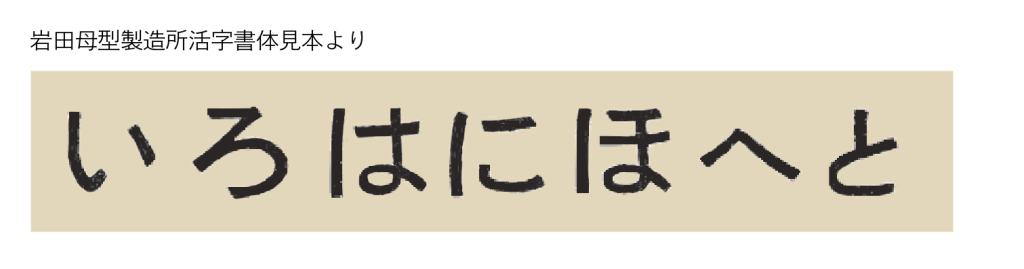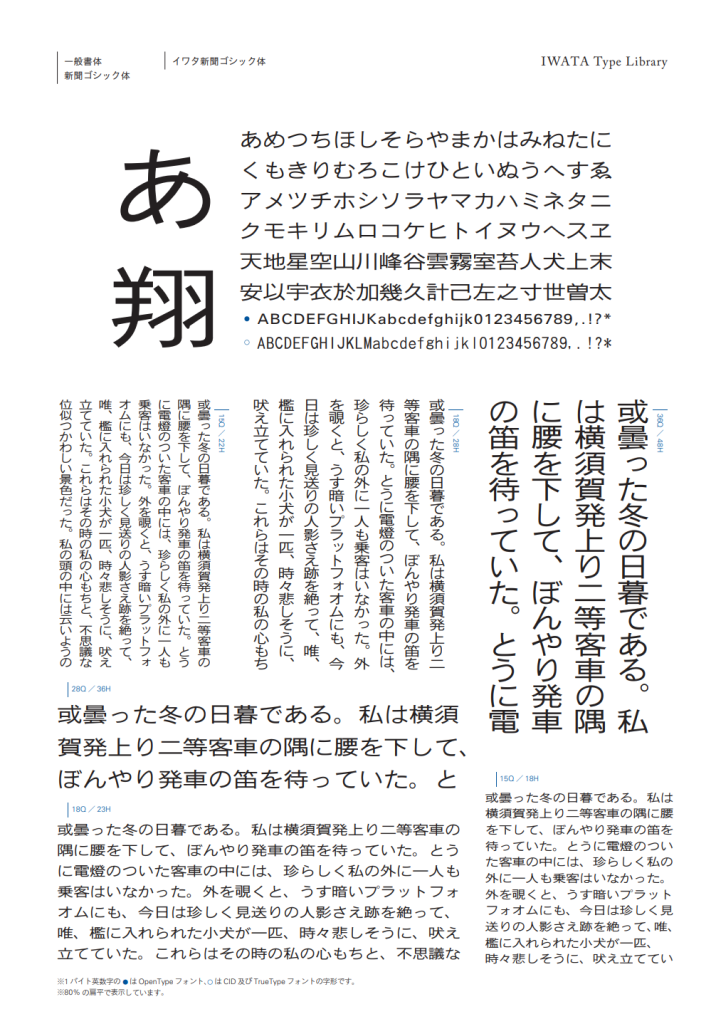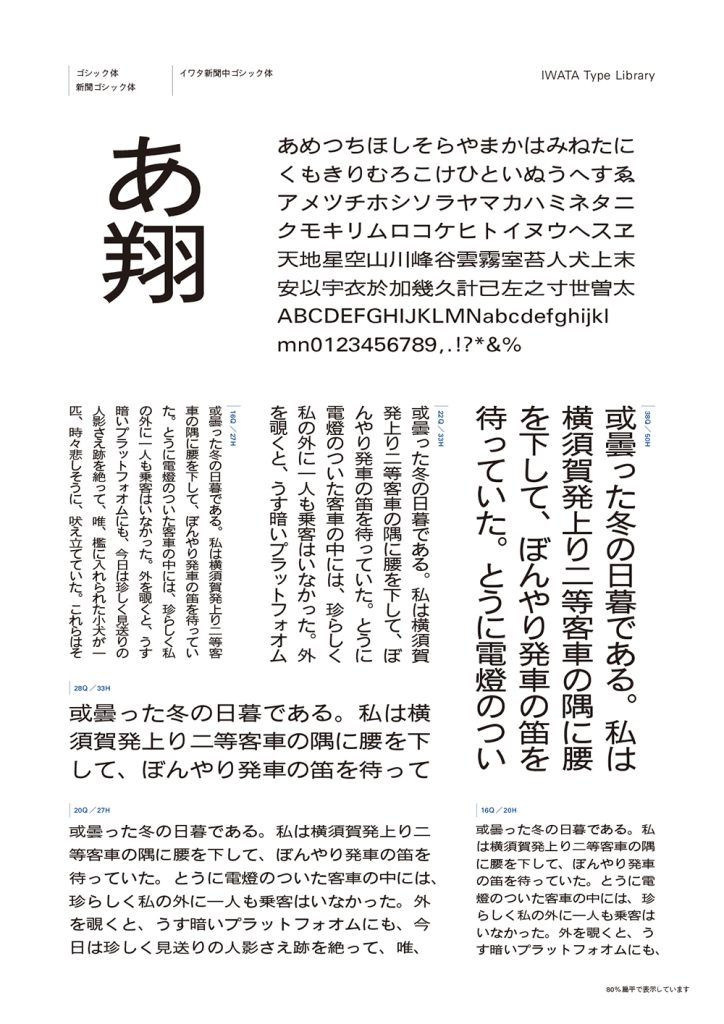
昭和16 年、イワタの前身である岩田母型製造所が開発した新聞用書体「岩田新聞呉竹体」を源流とする、歴史ある新聞ゴシック体でです。今でも多くの新聞社に採用され、また高い視認性から、広告コピーから小見出し、キャプションまで幅広く活用されています。80% 扁平に変形使用することを想定して設計されています。
「イワタ新聞ゴシック体」の仮名を現代風にアレンジした新がなもご用意しています。新聞ゴシック体の雰囲気を活かしながら、よりモダンさや明瞭さを感じられる書体です。
書体デザインのポイント
広めのふところと扁平を意識した縦横のバランス、流れるような美しいフォルムが特徴的です。
(扁平率:80%)